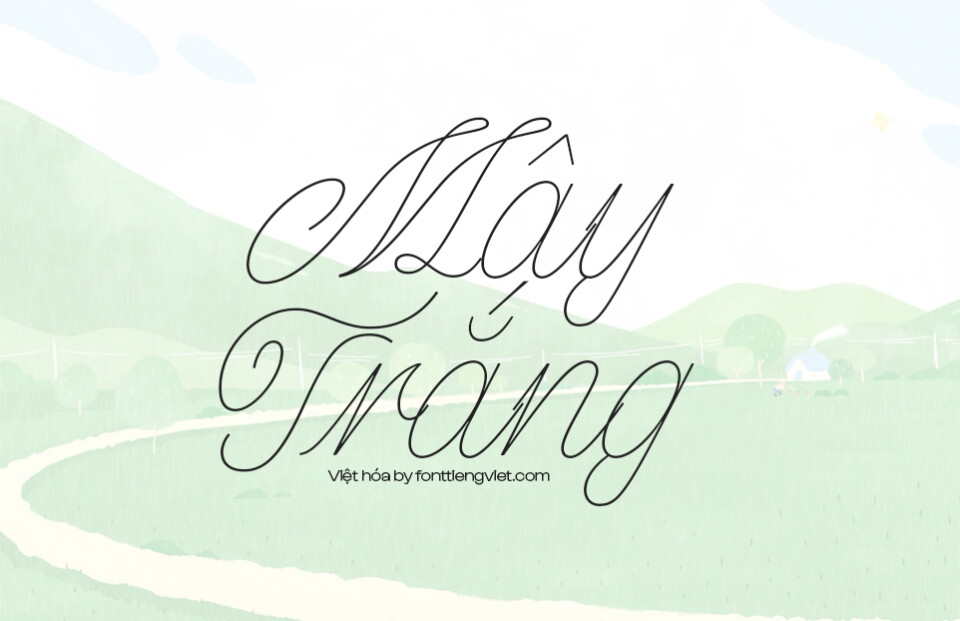
Trong thế giới thiết kế đồ họa đầy cạnh tranh ngày nay, việc lựa chọn một Font Chữ phù hợp có thể tạo nên sự khác biệt lớn cho tác phẩm của bạn. Đối với những nhà thiết kế tại Việt Nam, nhu cầu về các bộ font được Việt hóa hoàn chỉnh, đẹp mắt và chuyên nghiệp luôn ở mức cao. Và trong số đó, Font Việt hóa 1FTV Pencerio đã nhanh chóng nổi lên như một lựa chọn được yêu thích bởi sự tinh tế, độc đáo và khả năng ứng dụng đa dạng của nó. Đây không chỉ là một phông chữ thông thường mà còn là một công cụ mạnh mẽ giúp truyền tải thông điệp một cách rõ ràng và đầy cảm xúc, đặc biệt phù hợp với các dự án cần sự mềm mại nhưng không kém phần hiện đại. Việc sở hữu và sử dụng font này sẽ mở ra nhiều cơ hội sáng tạo mới, giúp các sản phẩm thiết kế của bạn trở nên thu hút và chuyên nghiệp hơn.
Khám Phá Sức Hút Đặc Biệt Của Font Việt hóa 1FTV Pencerio
Font Việt hóa 1FTV Pencerio nổi bật với phong cách viết tay hiện đại, mang đến sự kết hợp hoàn hảo giữa nét cổ điển và hơi thở đương đại. Các ký tự được thiết kế một cách tỉ mỉ, với đường nét mềm mại, uyển chuyển, tạo cảm giác thân thiện và gần gũi nhưng vẫn giữ được sự sang trọng cần thiết. Điều làm nên giá trị đặc biệt của Pencerio chính là quá trình Việt hóa chuyên nghiệp, đảm bảo mọi dấu câu, ký tự tiếng Việt đều được hiển thị một cách chính xác, đẹp mắt và nhất quán, không gặp phải lỗi font hay các vấn đề về hiển thị thường thấy ở các font chưa được Việt hóa. Sự chỉnh chu này giúp người dùng hoàn toàn yên tâm khi ứng dụng font vào các sản phẩm in ấn, thiết kế web, quảng cáo hay bất kỳ ấn phẩm truyền thông nào đòi hỏi sự hoàn hảo về mặt chữ viết.
Tại Sao Font Pencerio Việt Hóa Lại Được Ưa Chuộng?
Có nhiều lý do khiến Pencerio Việt hóa trở thành sự lựa chọn hàng đầu của nhiều nhà thiết kế. Đầu tiên, đây là một kiểu chữ mang tính thẩm mỹ cao, phù hợp với nhiều phong cách thiết kế khác nhau, từ tối giản, thanh lịch đến năng động, cá tính. Sự linh hoạt này cho phép font được sử dụng trong nhiều ngữ cảnh, từ logo, tiêu đề sách, thiệp mời, bao bì sản phẩm cho đến các bài đăng trên mạng xã hội. Thứ hai, khả năng đọc hiểu của Pencerio rất tốt, ngay cả khi được sử dụng ở kích thước nhỏ hay trong các đoạn văn bản dài, giúp thông điệp được truyền tải một cách hiệu quả nhất. Đây là một yếu tố quan trọng mà không phải font chữ đẹp nào cũng có thể đáp ứng được. Cuối cùng, việc tối ưu hóa cho tiếng Việt là một lợi thế không thể phủ nhận, loại bỏ mọi rào cản ngôn ngữ và kỹ thuật, giúp các nhà thiết kế Việt Nam có thể tự do sáng tạo mà không lo ngại về các vấn đề liên quan đến hiển thị ký tự.
Ứng Dụng Đa Dạng Của Font Chữ Pencerio
Font Việt hóa 1FTV Pencerio không chỉ đẹp mà còn vô cùng đa năng trong các dự án thiết kế. Bạn có thể sử dụng font này để tạo ra những logo độc đáo, mang đậm dấu ấn cá nhân hoặc thương hiệu. Trong lĩnh vực in ấn, Pencerio là lựa chọn tuyệt vời cho các tiêu đề báo, tạp chí, bìa sách, hay các ấn phẩm kỷ niệm. Đối với các thiết kế sự kiện như thiệp cưới, poster hội thảo, font này sẽ mang lại vẻ trang trọng và tinh tế. Ngoài ra, trong thiết kế web và giao diện người dùng, Pencerio giúp các website và ứng dụng trở nên thân thiện và dễ đọc hơn, nâng cao trải nghiệm người dùng. Với sự hỗ trợ đầy đủ các ký tự tiếng Việt, font còn rất phù hợp cho việc thiết kế các bài thuyết trình, infografic hoặc các tài liệu học tập, giúp thông tin được trình bày một cách rõ ràng và hấp dẫn. Các dự án cá nhân như viết blog, tạo hình ảnh minh họa cũng sẽ được hưởng lợi rất nhiều từ sự duyên dáng của Pencerio.
Lợi Ích Khi Sử Dụng Font Việt Hóa Chuẩn
Việc sử dụng một font Việt hóa chuẩn như Pencerio mang lại nhiều lợi ích thiết thực. Quan trọng nhất là nó đảm bảo tính nhất quán và chuyên nghiệp cho tất cả các sản phẩm thiết kế của bạn. Không còn tình trạng lỗi font, mất dấu hay hiển thị sai ký tự, giúp tiết kiệm thời gian chỉnh sửa và đảm bảo chất lượng hình ảnh thương hiệu. Một font chữ đẹp và chuẩn còn góp phần nâng cao giá trị thẩm mỹ của tác phẩm, tạo ấn tượng mạnh mẽ với người xem và truyền tải thông điệp một cách hiệu quả hơn. Hơn nữa, việc này còn thể hiện sự tôn trọng đối với ngôn ngữ và văn hóa Việt Nam, đặc biệt khi các sản phẩm được sử dụng trong môi trường công cộng hoặc kinh doanh.
Với những ưu điểm vượt trội về mặt thẩm mỹ và tính năng, Font Việt hóa 1FTV Pencerio chắc chắn là một tài sản quý giá cho bất kỳ nhà thiết kế nào. Đây không chỉ là một phông chữ đẹp mà còn là một công cụ mạnh mẽ giúp bạn tạo ra những tác phẩm độc đáo, chuyên nghiệp và đầy ấn tượng. Đừng ngần ngại trải nghiệm và đưa Pencerio vào bộ sưu tập Font Chữ của mình để nâng tầm mọi dự án thiết kế. Nó sẽ là một người bạn đồng hành đáng tin cậy, giúp bạn biến những ý tưởng sáng tạo thành hiện thực một cách hoàn hảo nhất.